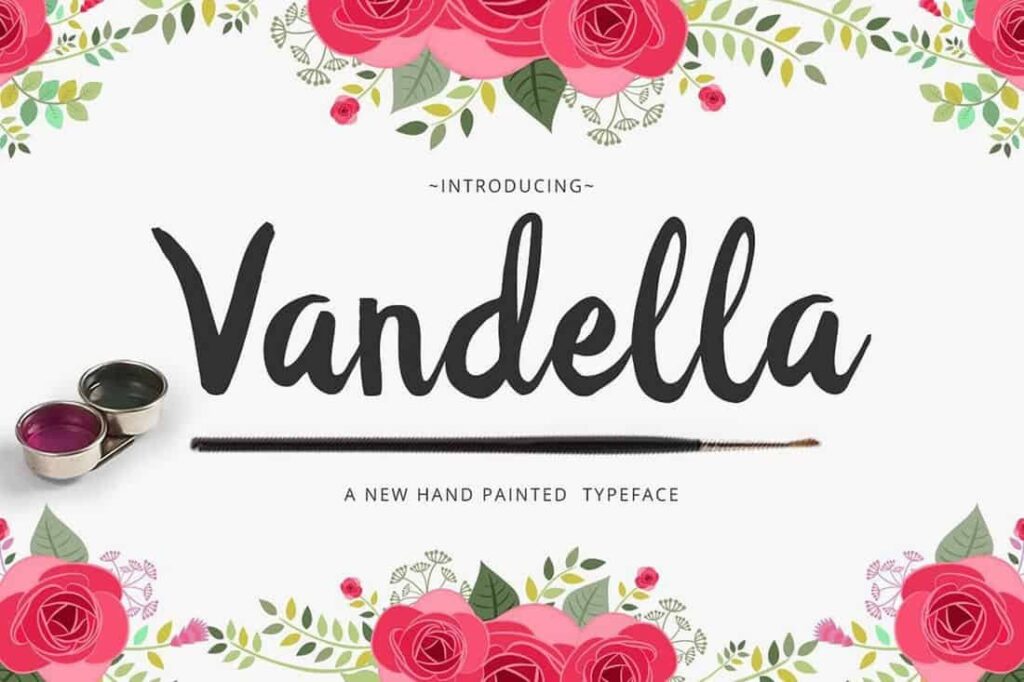
Venlige Skrifttyper: Skab Varme & Imødekommenhed
I typografiens verden findes der skrifttyper, der føles som en varm velkomst. De er ikke stive eller formelle, men derimod indbydende, tilgængelige og fulde af personlighed. Disse kaldes ofte 'venlige skrifttyper'. De har en særlig evne til at skabe en følelse af nærhed og lethed, hvilket gør dem ideelle til en lang række kreative og personlige projekter, såvel som til branding, der ønsker at fremstå legesyg og uformel. At vælge den rigtige skrifttype er afgørende for at formidle den ønskede tone i din kommunikation, og de venlige skrifttyper tilbyder et unikt sæt værktøjer til at opnå netop dette.
De visuelle træk ved venlige skrifttyper adskiller dem markant fra mere traditionelle eller formelle skrifttyper. Hvor sidstnævnte ofte lægger vægt på stramhed, struktur og autoritet, fokuserer venlige skrifttyper på blødhed og åbenhed. Disse forskelle er ikke blot æstetiske; de påvirker direkte, hvordan vi opfatter den tekst, vi læser, og dermed det budskab, der formidles. Forståelsen af disse forskelle er nøglen til effektivt at udnytte venlige skrifttypers potentiale i dit designarbejde.
Hvad Karakteriserer En Venlig Skrifttype?
Venlige skrifttyper er let genkendelige på grund af en række fællestræk, der bidrager til deres imødekommende udtryk. Det mest fremtrædende træk er ofte deres afrundede former. I stedet for skarpe hjørner og strenge, lige linjer ser man bløde kurver og jævne overgange. Tænk på bogstaver som 'o', 'c', 's' – i venlige skrifttyper vil disse former være særligt runde og flydende. Selv bogstaver, der typisk har lige strøg som 'l', 'i' eller 'n', kan have let afrundede ender eller 'terminaler'.
Ud over afrundede former har venlige skrifttyper typisk også åbne former. Dette betyder, at åbningerne i bogstaver som 'a', 'e' og 'c' er relativt store og uhindrede. Denne åbenhed giver skrifttypen et luftigt og lyst udseende, hvilket igen bidrager til følelsen af lethed og tilgængelighed. En lukket form kan føles klaustrofobisk eller stram, mens en åben form inviterer øjet ind.
En tredje vigtig faktor er generøs afstand mellem bogstaverne (kendt som kerning og tracking). Venlige skrifttyper undgår typisk meget stram bogstavafstand. Lidt ekstra plads mellem tegnene gør teksten mindre tæt og mere afslappet at se på. Dette understøtter yderligere den overordnede følelse af ro og tilgængelighed, i modsætning til den tæthed, der kan signalere effektivitet eller hastværk i andre skrifttyper.
Mange venlige skrifttyper er sans-serif, hvilket betyder, at de mangler de små 'fødder' eller strøg (seriffer), man finder på enderne af bogstaver i skrifttyper som Times New Roman. Fraværet af seriffer kan gøre skrifttypen renere og mere moderne i sit udtryk, hvilket ofte associeres med en mere afslappet tone. Nogle venlige skrifttyper kan dog have seriffer, men i så fald er de ofte bløde og afrundede, ikke skarpe og strukturelle.
Samlet set er formålet med disse designvalg at skabe en visuel oplevelse, der er behagelig, afslappet og blottet for den stivhed, der kan findes i mere traditionel typografi. De signalerer 'du er velkommen her' og 'dette er ikke alt for seriøst', hvilket er værdifuldt i mange designkontekster.
Hvorfor Føles Runde Former Venlige? Psykologien Bag
Intuitionen fortæller os måske, at runde former føles blødere og mere indbydende end skarpe vinkler, men der er faktisk psykologiske principper, der understøtter denne opfattelse. Selvom der ikke er omfattende forskning specifikt på 'venlige skrifttyper', findes der studier, der undersøger vores reaktioner på former generelt – selve grundlaget for typedesign.
En af de mest relevante observationer er, at rundhed ofte opfattes som mere smukt eller æstetisk tiltalende end skarphed. Dette kan have rødder i vores evolutionære historie, hvor bløde, organiske former (som dem i naturen) potentielt blev associeret med sikkerhed og næring, mens skarpe, kantede former (som klipper eller våben) kunne signalere fare.
Derudover viser studier, at forskellige geometriske former kan skabe forskellige atmosfærer. Runde eller cirkulære former associeres ofte med fællesskab, helhed, blødhed og tryghed. I modsætning hertil kan kantede eller trekantede former associeres med dynamik, fare, eller effektivitet. Når disse principper overføres til bogstaver, er det naturligt, at skrifttyper domineret af bløde kurver og afrundede ender vil fremkalde en følelse af varme og tilgængelighed.
Et fascinerende psykologisk fænomen, der understreger sammenhængen mellem lyd, form og følelse, er Bouba-Kiki Effekten. Denne effekt demonstrerer, hvordan mennesker intuitivt forbinder visse lyde med visuelle former, uafhængigt af sproglig baggrund. Når forsøgspersoner præsenteres for to abstrakte former – en blød, afrundet form og en skarp, takket form – og to nonsensord, "Bouba" og "Kiki", vil et overvældende flertal associerer "Bouba" med den afrundede form og "Kiki" med den takkede form. Dette antyder, at der er en fundamental, tværkulturel forbindelse mellem lyde, der lyder 'bløde' (som 'ou' og 'b'), og visuelt bløde former, samt mellem lyde, der lyder 'skarpe' (som 'i' og 'k'), og visuelt skarpe former. Overført til typografi kan man argumentere for, at skrifttyper, der visuelt 'lyder' som "Bouba" (med deres bløde, runde former), naturligt opfattes som mere venlige og imødekommende end dem, der 'lyder' som "Kiki" (med deres skarpe, kantede former).